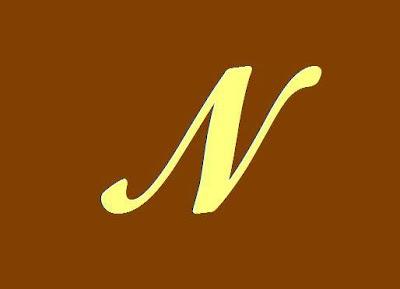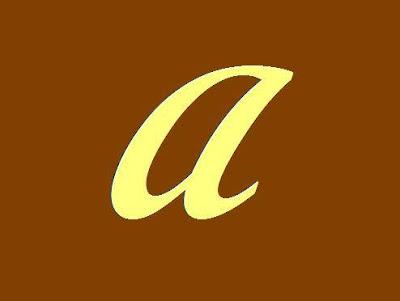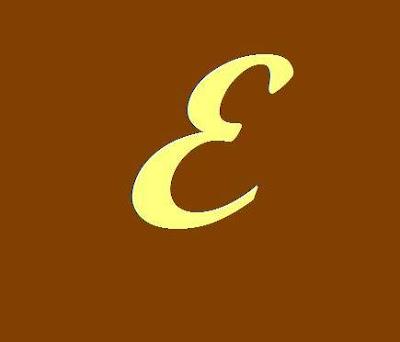
Welche Schrift könnte das sein?
Leider habe ich nur diesen Auszug bekommen, die würde aber wirklich gut passen! vielen dank.
… Zigarrenbrand Eibe …
Was für eine Schriftmischung! :-o
Hier haben echte Profis etikettiert.
Gebe R::bert recht. Sieht aber wie eine verzerrte Script MT Bold von F.H. Stelzer aus.
Die obigen unterschiedlichsten Beispiel sprechen eigentlich gegen eine verzerrte Schrift.